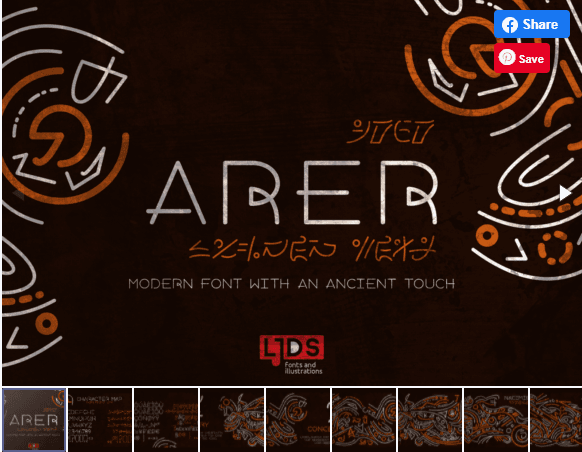
Arer Font
Arer - это минималистичный дисплей с тонкими буквами. Его можно легко сопоставить с невероятно большим набором проектов, поэтому добавьте его к своим творческим идеям и обратите внимание, как они выделяются среди них!